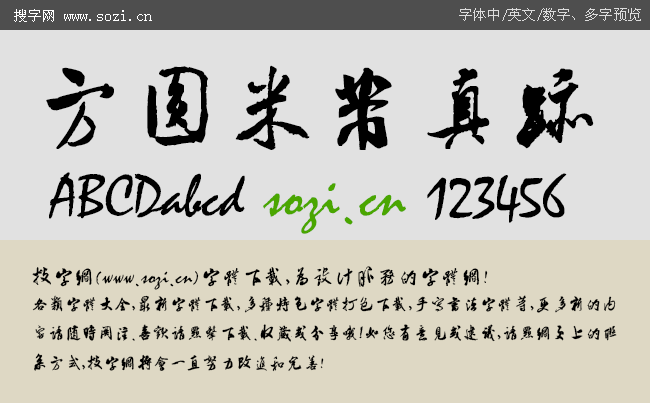
方圓米芾真跡
搜字網(wǎng)提供一款書法字體方圓米芾真跡下載,米芾書法字的起筆往往頗重,到中間稍輕,遇到轉(zhuǎn)折時提筆側(cè)鋒直轉(zhuǎn)而下。重視整體氣韻,兼顧細(xì)節(jié)的完美,可適用于繪畫設(shè)計、廣告設(shè)計、平面設(shè)計、個性簽名等領(lǐng)域。